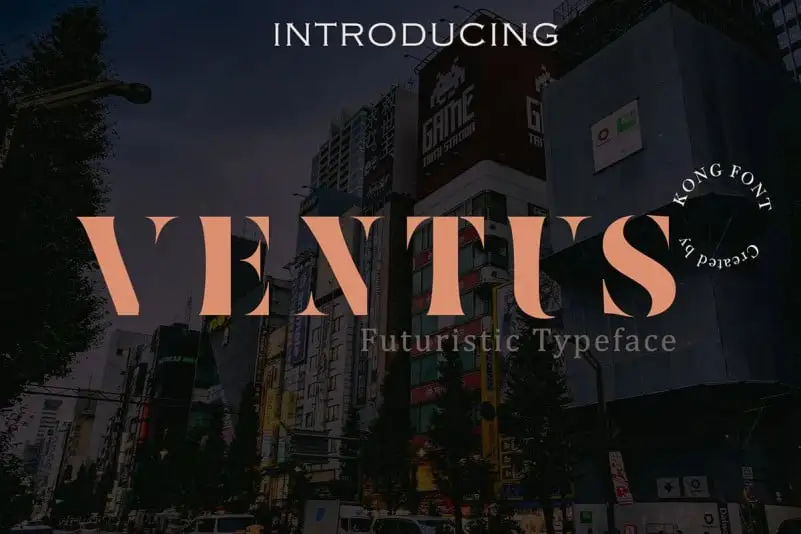
Ventus Display Font – Download Grátis
A fonte Ventus Display Font é uma tipografia serifada que carrega um estilo clássico modernizado. Ela foi criada pela Fontkong e é ideal para múltiplas aplicações, desde logotipos de marca até headlines e monogramas. Suas qualidades femininas e masculinas a tornam versátil, perfeita para uso em nomes iniciais ou marcas que desejem um aspecto sofisticado, simples e caro. Neste fonte modernizada está o resultado de combinar elementos clássicos com uma aparência leve e elegante. Seja você ou sua marca, a Ventus Display Font oferece uma maneira moderna de expressar feminilidade e masculinidade, tornando-a perfeita para aplicações que buscam um equilíbrio entre sofisticação e clareza. Com esse fonte à mão, você pode criar marcas elegantes e impecáveis em qualquer situação.